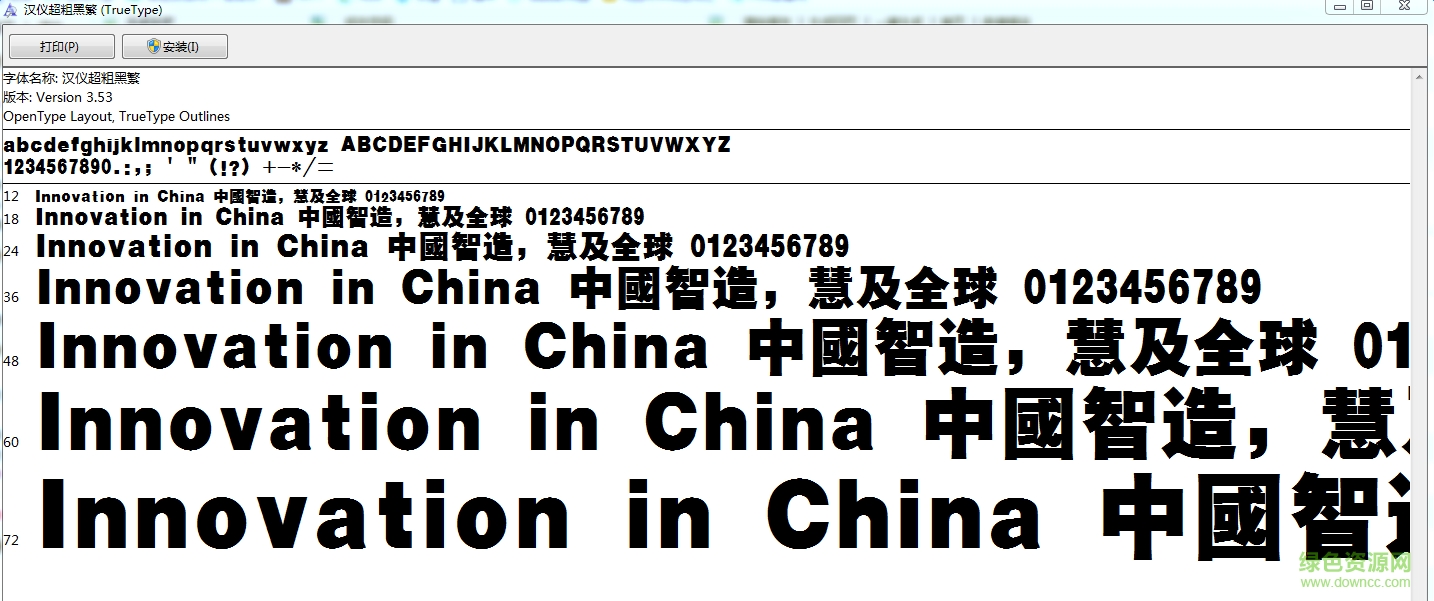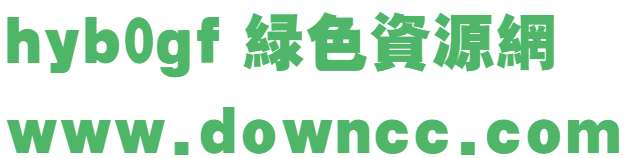
hyb0gf
hyb0gf字體又名漢儀超粗黑繁,是一款壯重醒目的漢儀黑體字體,結(jié)構(gòu)端正,號(hào)召力較強(qiáng),應(yīng)用效果良好,需要繁體字體的朋友快來綠色資源網(wǎng)下載吧!
hyb0gf字體特點(diǎn)
漢儀超粗黑簡(jiǎn)保持著黑體字的共有特點(diǎn),筆畫粗壯有力,橫豎筆畫粗細(xì)比較接近,兩端平直,加鋒較小,筆畫簡(jiǎn)潔粗壯!
hyb0gf